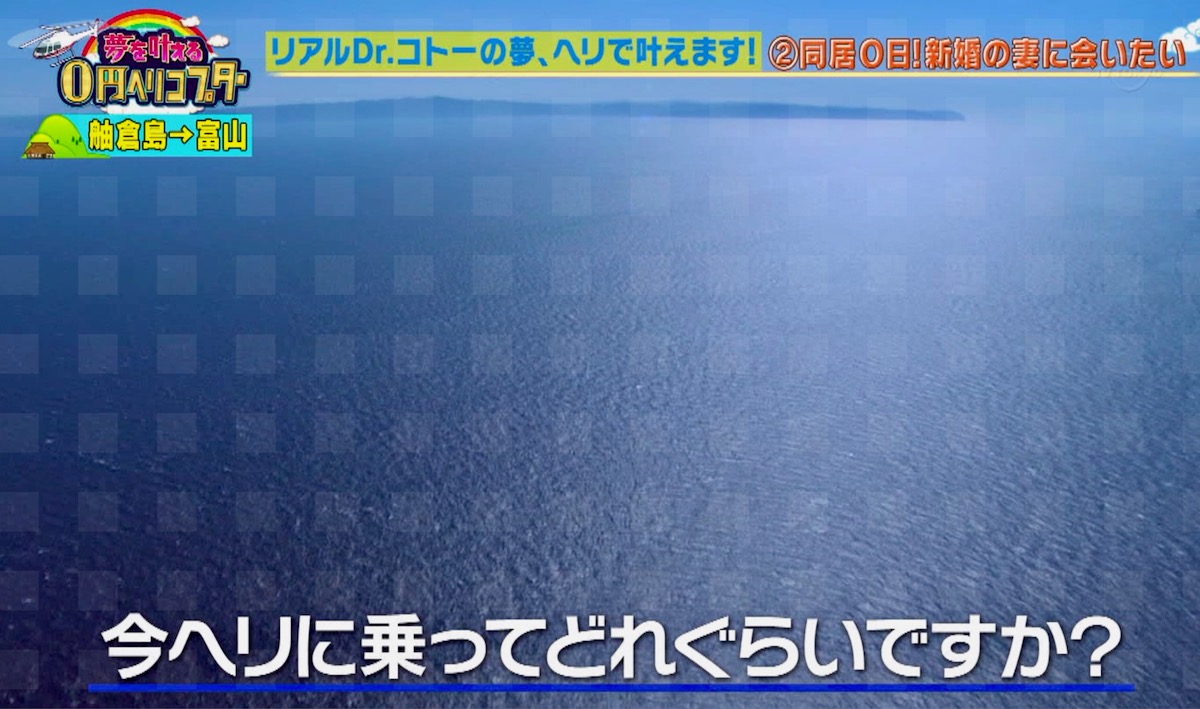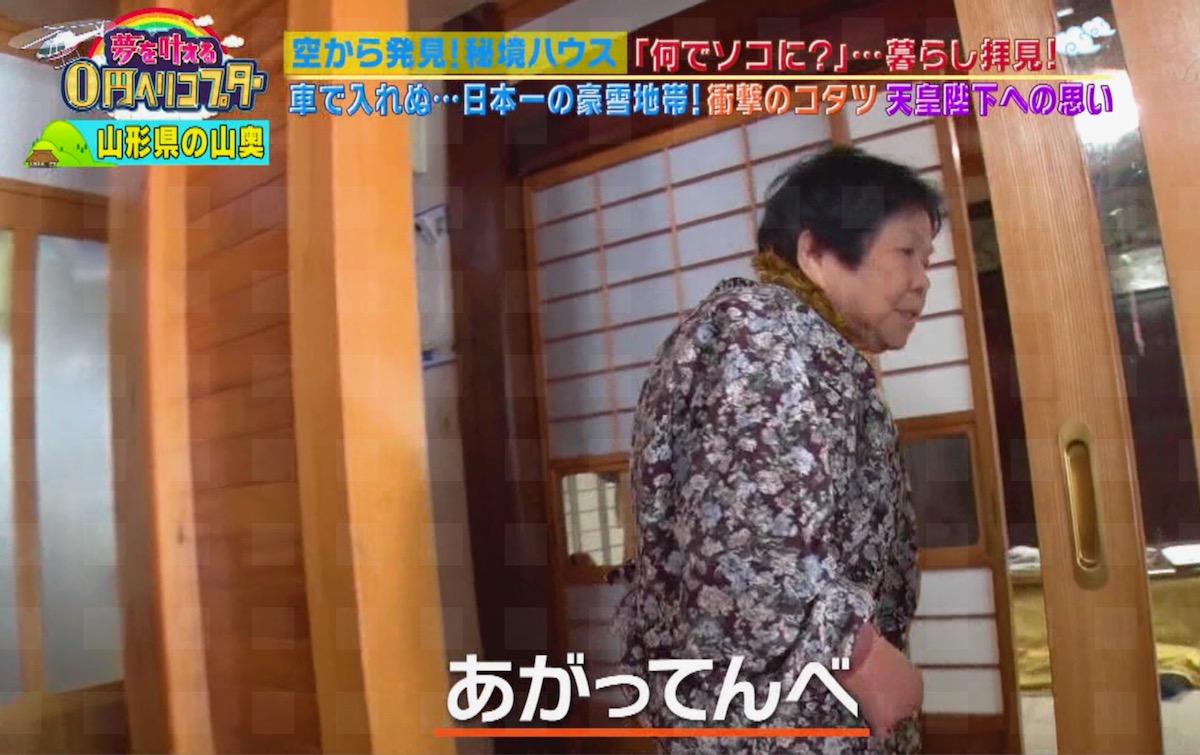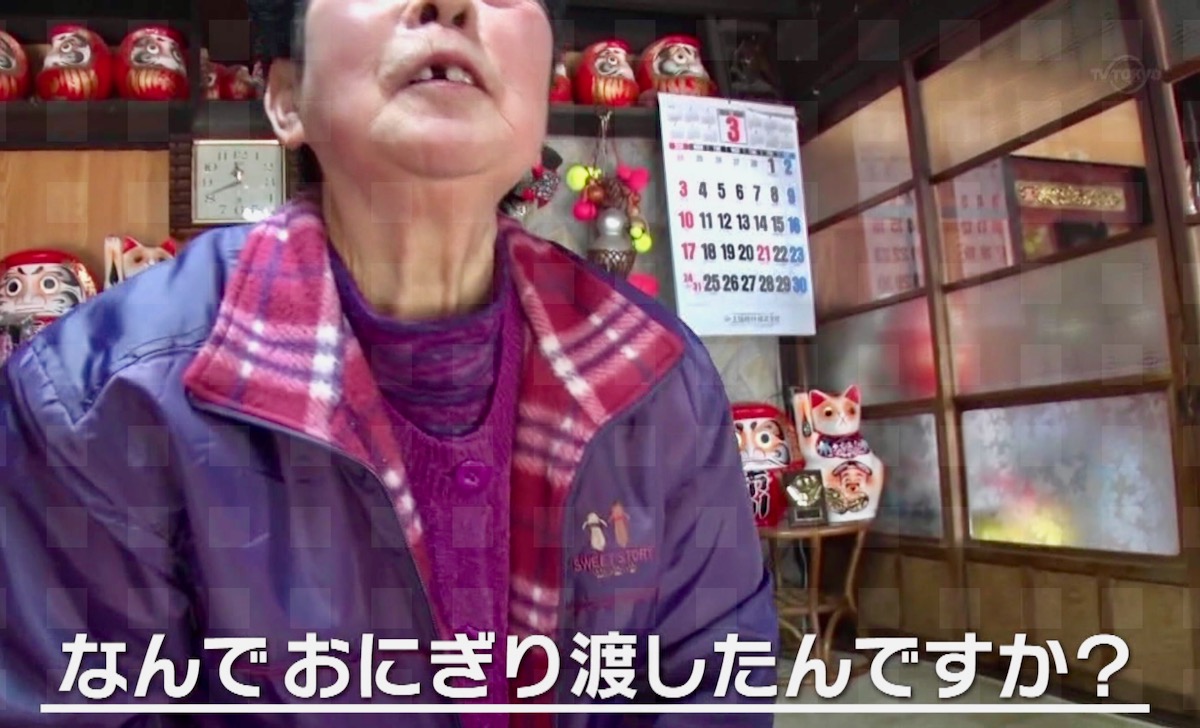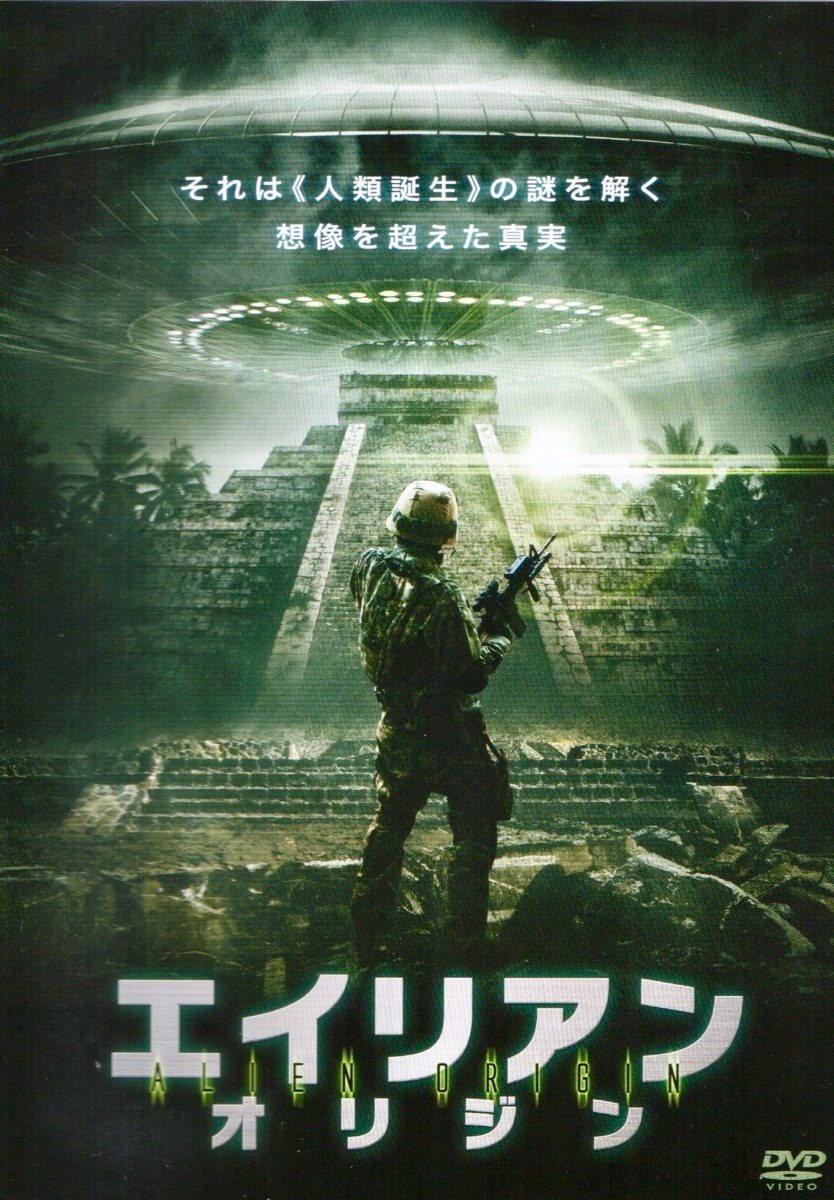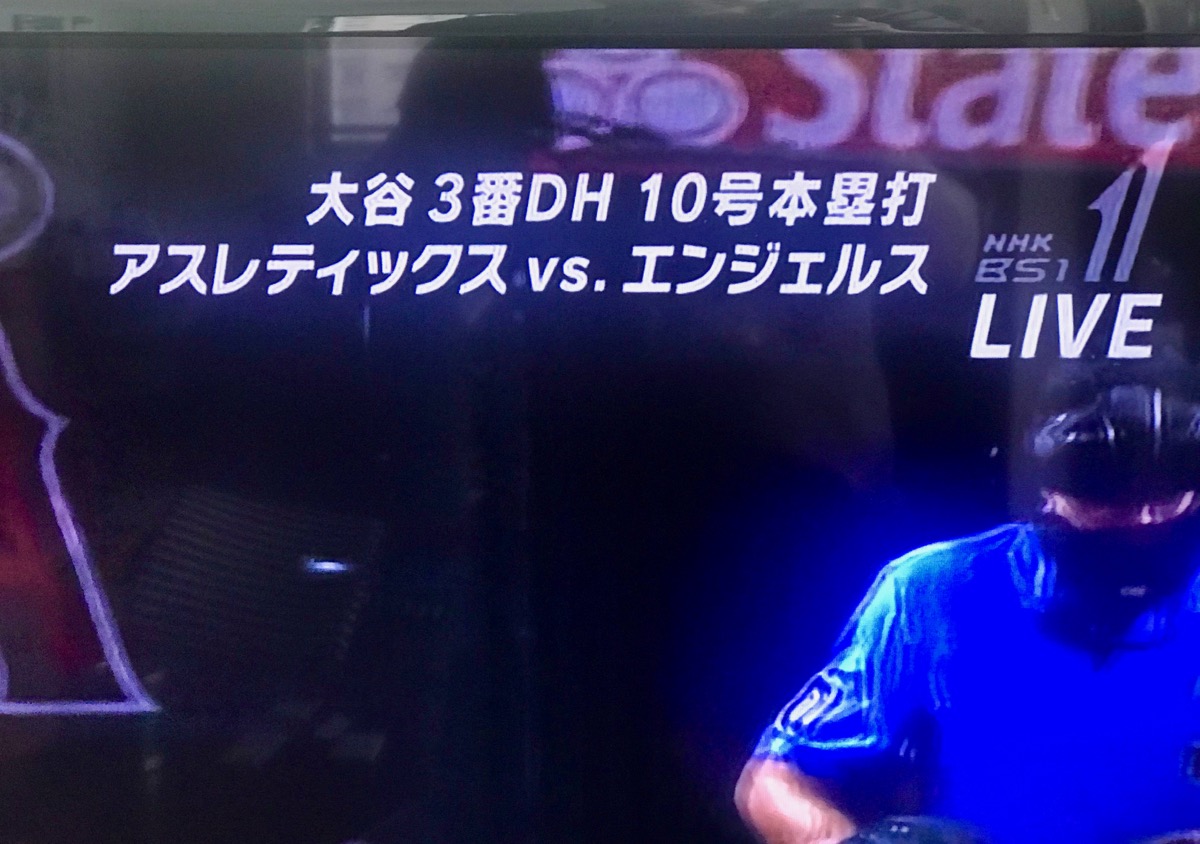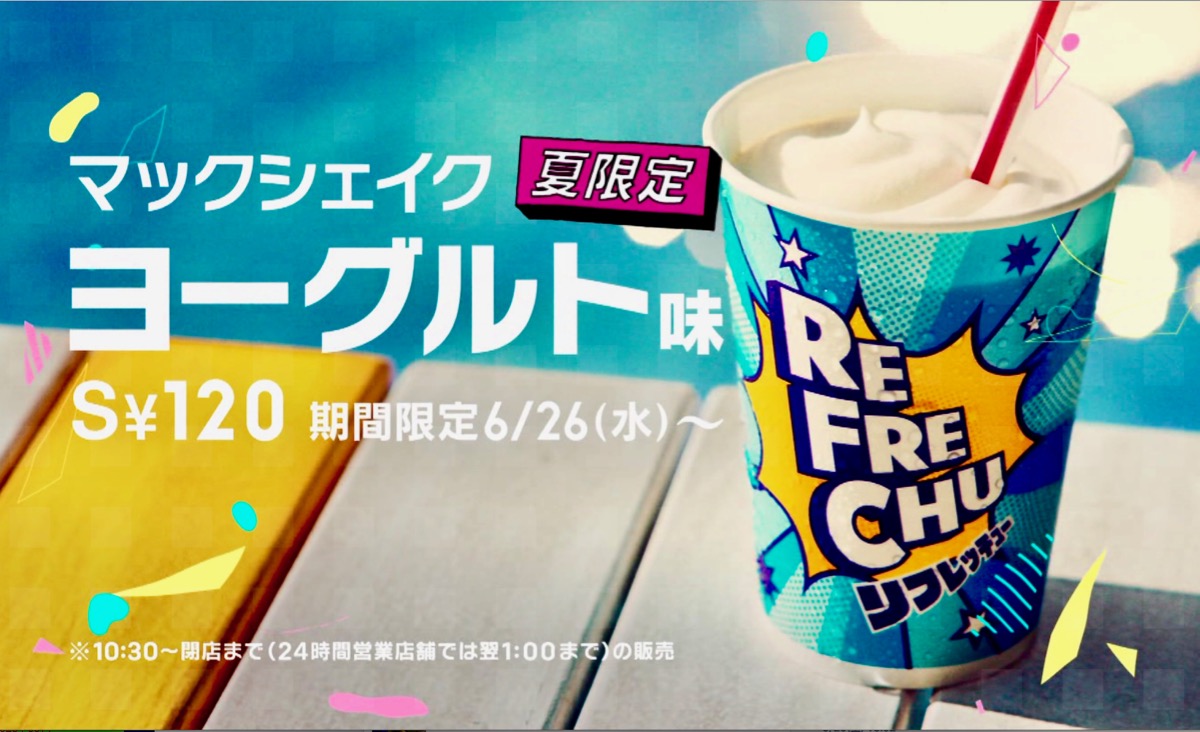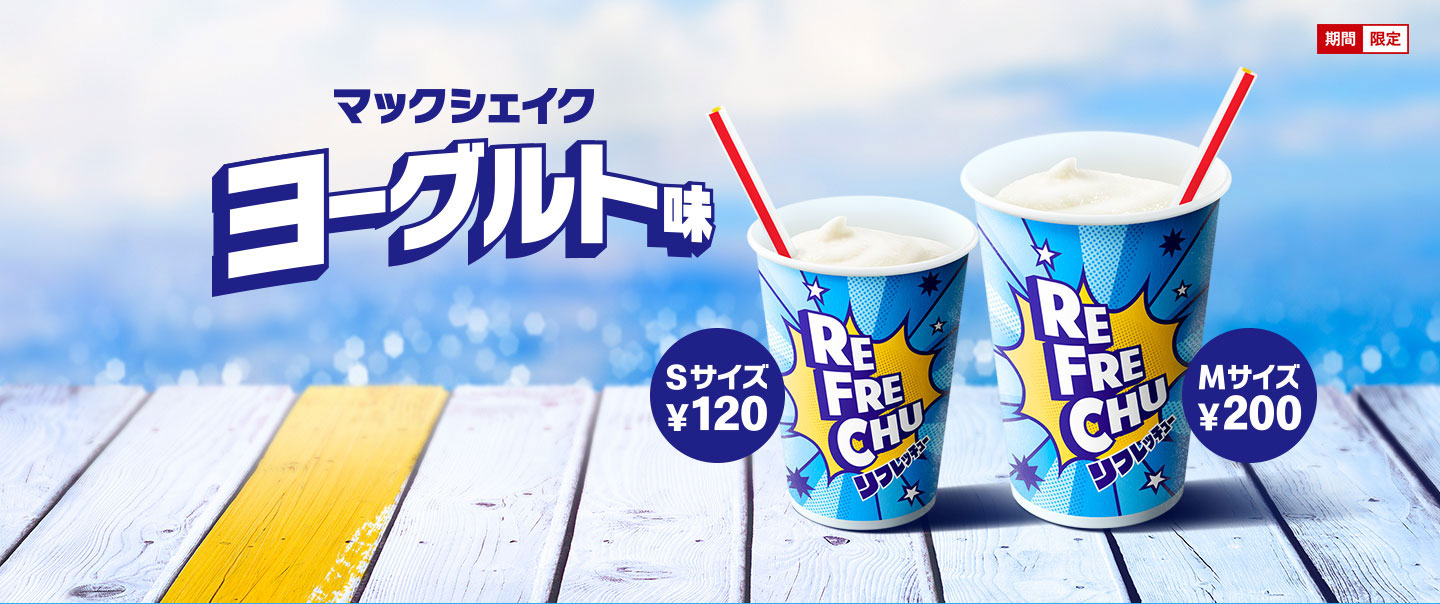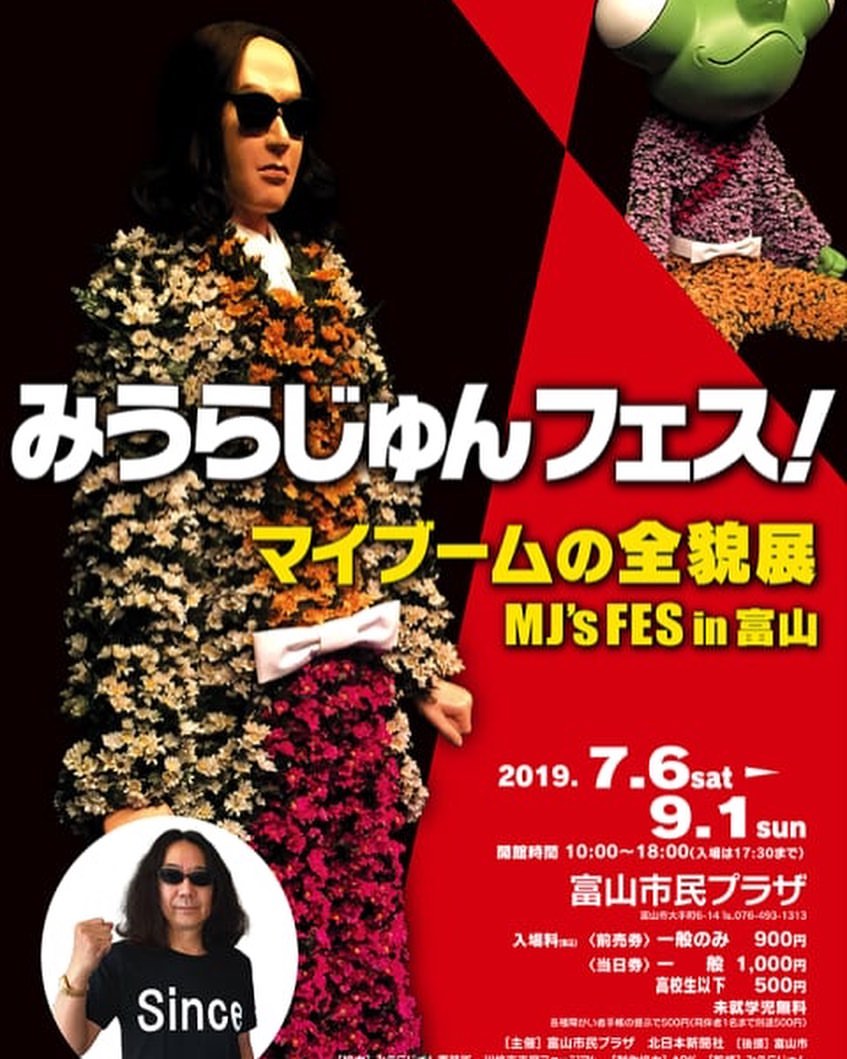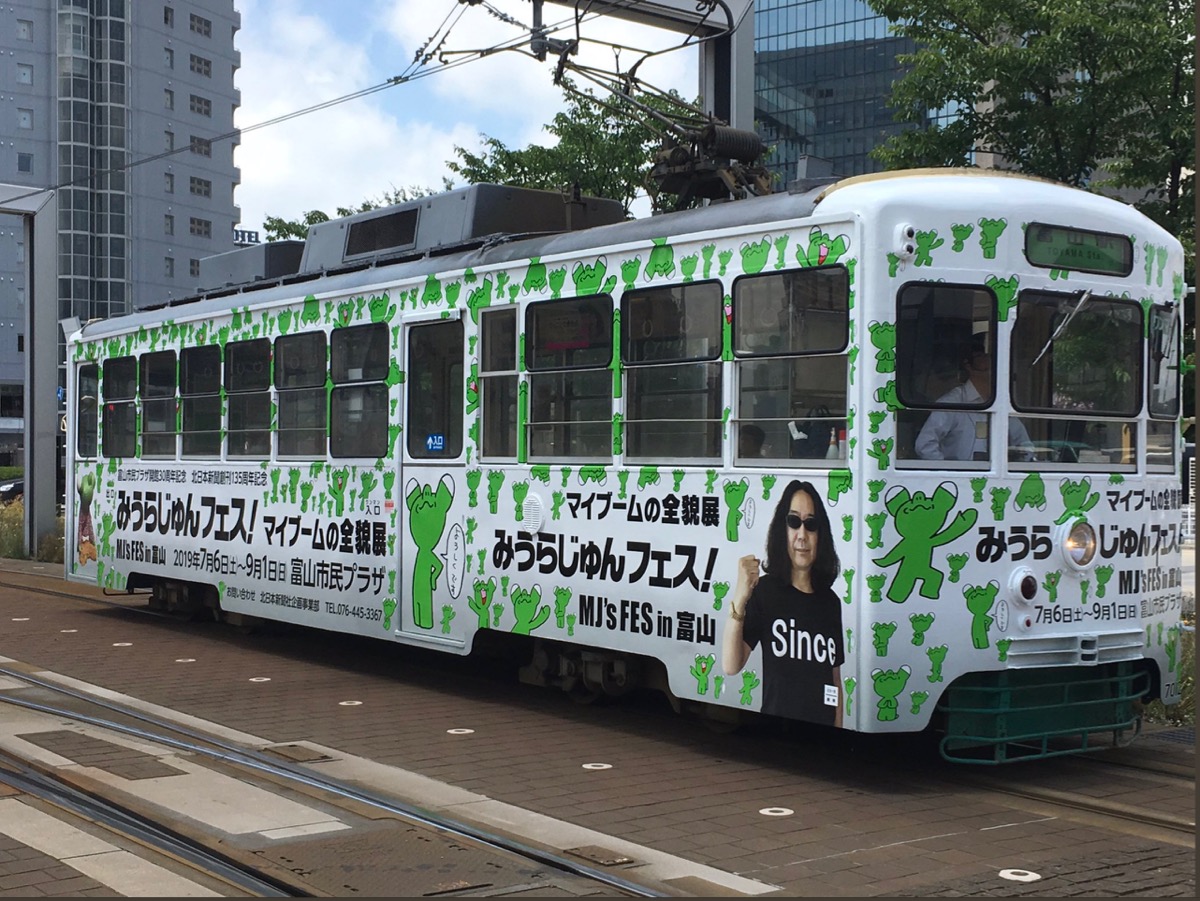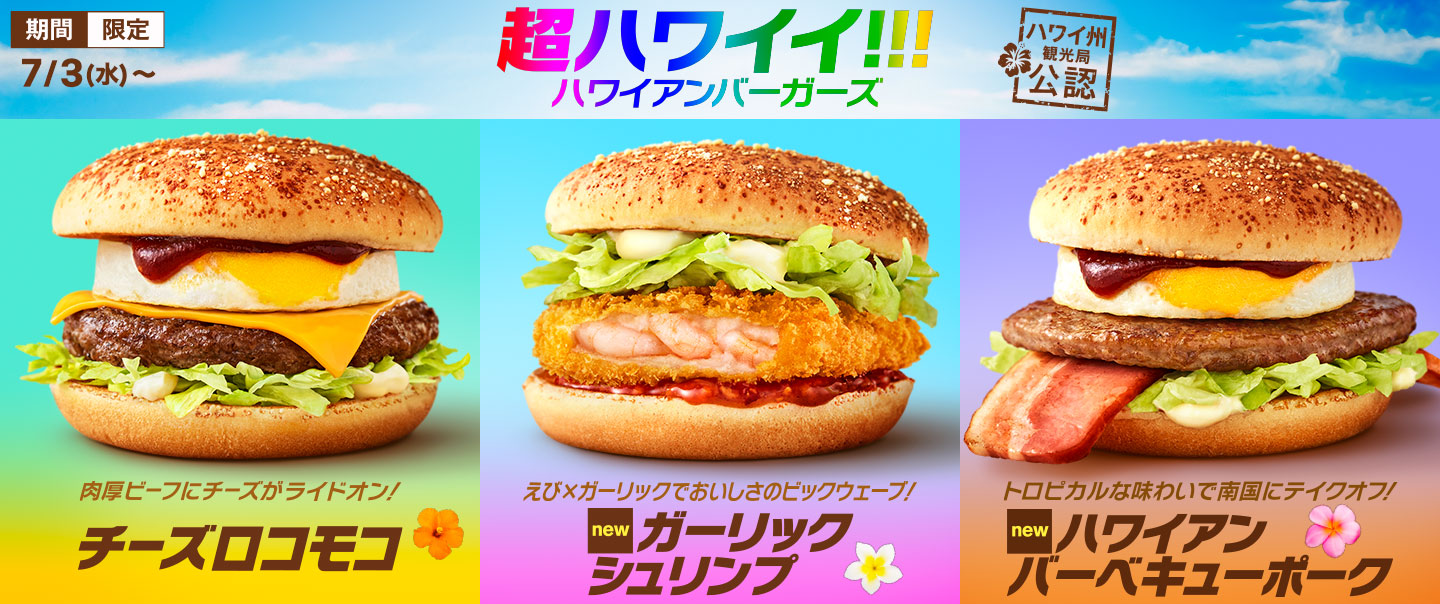
アニラジ  さとうゆたか  2020年3月18日(水) 11:10
アニメ声優がパーソナリティを務めるラジオのことを「アニラジ」というらしい。
これも…。
もう1点。
広報誌のロゴ  さとうゆたか  2020年3月10日(火) 17:08
山梨県の広報誌「ふれあい」。
本の表紙  さとうゆたか  2020年2月28日(金) 14:34
書名:マインドフルネス入門
著者:大田健次郎
発行:清流出版
テレビCM  さとうゆたか  2020年2月25日(火) 10:53
マクドナルドのビッグマックジュニア。
これも…。
本の表紙  さとうゆたか  2020年2月22日(土) 9:27
書名:すみれベーカリーのカナリアパン
著者:古田節子、山岡勝司
発行:銀の鈴社
FM802のサイト内画像  takumi  2020年2月18日(火) 20:29  HP
佐藤さん、こんばんは。
FM802(大阪のラジオ局)のサイト内に掲載されている画像で「ニタラゴルイカ」が使われています。
さらにこれも。
これは等幅フォントですね。
(これだけ見ると普通にルイカですが、たぶん同じニタラゴルイカでしょう)
最後にもう1枚。
下の小さくて黒い文字は他社フォントですが。
大阪のラジオ局のサイト…。
なかなか見に行くことはないので、貴重です。
リーフレット  さとうゆたか  2020年2月11日(火) 9:07
郵便局で。
テレビ番組  さとうゆたか  2020年2月6日(木) 9:41
テレビ東京の「お米あるんですけど…?」。
フチと影をつけて、はっきりくっきり!
もう1点。
YouTubeチャンネル  さとうゆたか  2020年2月2日(日) 9:55
ゆとなみTV。
ニタラゴルイカがたくさん使われています!
これとか…。
本の表紙  さとうゆたか  2020年1月27日(月) 9:12
書名:勝つサッカー フォワード
著者:豊田 陽平
発行:メイツ出版